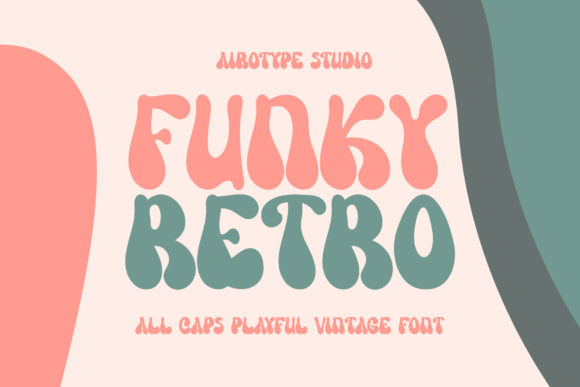
Funky Retro
Funky Retro – A Fonte Vintage que Revoluciona seu Design
Se você está em busca de uma fonte vintage que una o charme dos anos 70 com a energia contemporânea, Funky Retro é a escolha ideal. Em letras all‑caps, ela traz um estilo bold, sweet, cute e dinâmico, perfeito para quem quer destacar projetos com personalidade e atitude.
- Design marcante: A tipografia em caixa alta garante alta legibilidade e presença visual, ideal para logotipos que precisam chamar atenção imediatamente.
- Versatilidade criativa: Seja para crafting, posters, branding, stickers ou sublimação, Funky Retro se adapta a diferentes formatos sem perder o impacto.
- Estilo retro moderno: Combina o toque nostálgico dos anos 60/70 com linhas atuais, oferecendo um visual retro‑futurista que agrada tanto a públicos jovens quanto a amantes do vintage.